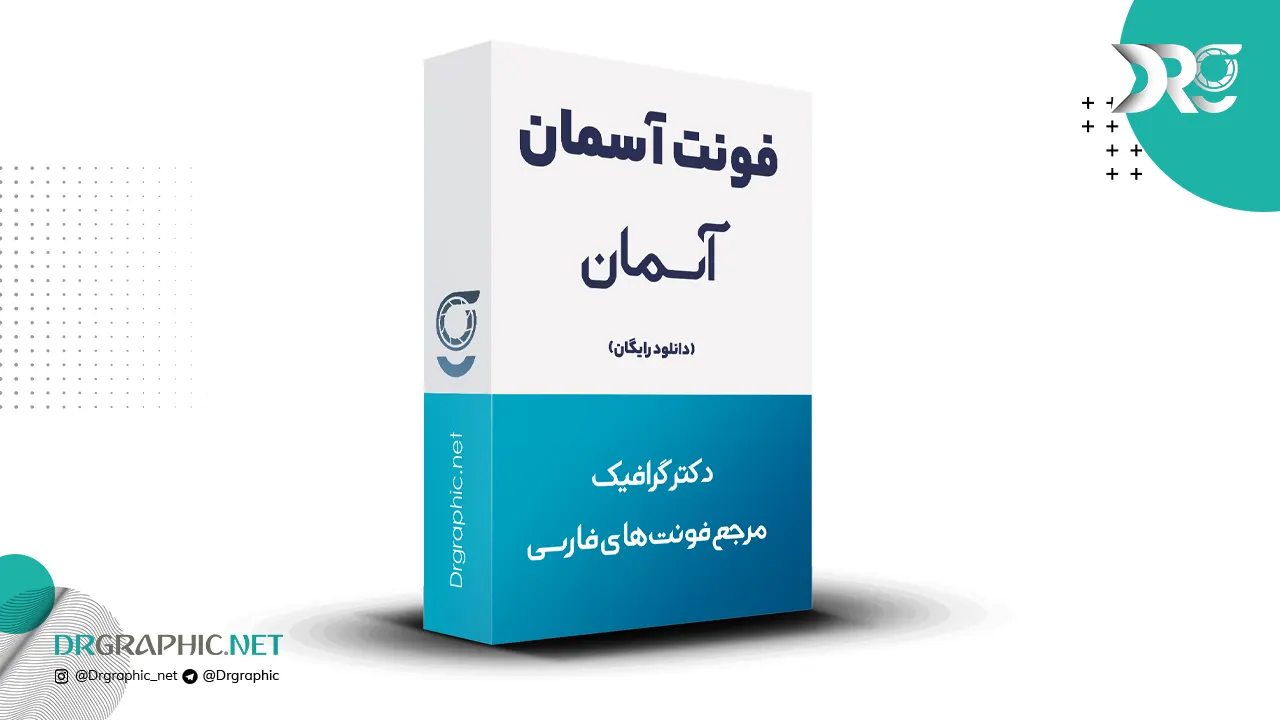
فونت آسمان ( G Aseman ) از سری فونت های تایپوگرافی می باشد. فونت آسمان یکی از زیبا ترین و حرفه ای ترین فونت های رایگان فارسی میباشد که میتوانید با لینک مستقیم نسخه کاملا تست شده و سالم این فونت را دانلود کنید.
نمونه نوشته با این فونت: